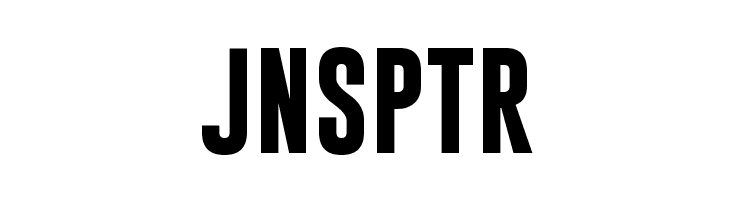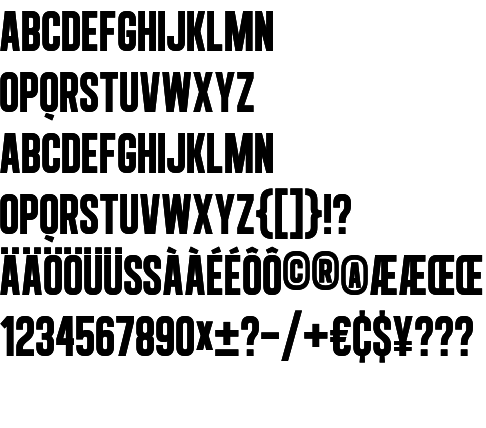
Finde die richtige Schriftart nicht heraus
ich suche schon eine Weile nach der richtigen Schriftart, habe auch schon bei "MyFonts" bzw. "WhatTheFont" geschaut, aber das Tool erkennt nicht so wirklich die Schriftart, da "PTR" zu dicht aneinander sind und es als ein Buchstabe erkannt wird :(
Kann mir dennoch von euch sagen, um welche Schriftart es sich dabei handelt?
das Tool erkennt nicht so wirklich die Schriftart, da "PTR" zu dicht aneinander sind und es als ein Buchstabe erkannt wird :(
:tuschel: Dann mussudas auseinanderschnippeln. ;-)  Anders machen das die Experten hier im Forum auch nicht.
Nur mal so als Hinweis. Nicht böse gemeint. :schonklar: Es kann ja auch sein, dass jemand hier die Schrift zufällig auf  einen Blick erkennt.
Ganz nahe dran ist die Bebas Kai von Flat-IT tippen. Das ist eine ausgebaute Bebas (alte).
Aber sie ist es nicht. Ich habe da einen Verdacht ...
Alégre Sans NC Version 1.05 vom 24. Juli 2011 in Bold:
Die Gobold wäre auch nah dran. Vielleicht ist sie’s auch, da gibt’s so viele fast identische.